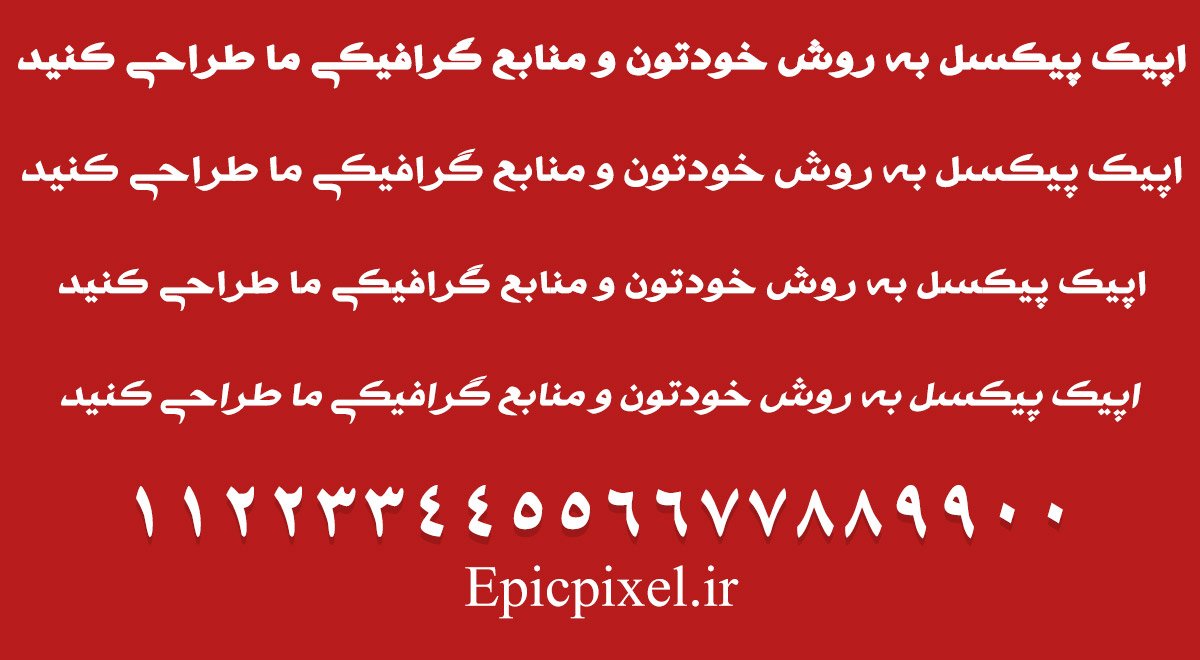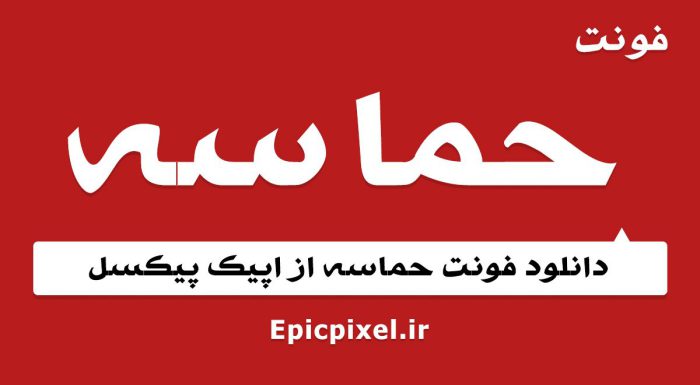
فونت حماسه فارسی
فونت حماسه، با الهام از فونت محبوب تهران و با تغییراتی ظریف و افزودن عناصر گرافیکی انقلابی، ظاهری قدرتمند و منحصربه فرد به نوشته های شما می بخشد. این فونت، با وجود شباهت هایی به فونت تهران، هویتی مستقل دارد و برای طراحی هایی که نیازمند جلوه ای خاص و متمایز هستند، گزینه ای ایده آل به شمار می رود.
یکی از ویژگی های برجسته فونت حماسه، خوانایی بالای آن در اندازه های مختلف است. چه در عناوین بزرگ و چه در متن های طولانی، حروف این فونت به راحتی قابل تشخیص هستند و تجربه خواندن را بهبود می بخشند. این ویژگی، فونت حماسه را برای استفاده در طراحی های چاپی و دیجیتال، از جمله پوسترها، بنرها، وب سایت ها و اپلیکیشن ها، مناسب می سازد.
فونت حماسه، با وجود ظاهر قدرتمندش، در برخی موارد ممکن است برای متن های بسیار طولانی و با اندازه کوچک، کمی سنگین به نظر برسد. با این حال، این ویژگی در اکثر کاربردها، به خصوص در عناوین و متن های کوتاه، نه تنها نقطه ضعف نیست، بلکه به جذابیت و تأثیرگذاری بیشتر طرح کمک می کند. اگر به دنبال فونتی هستید که هم رایگان باشد و هم به طرح هایتان روحی تازه ببخشد، فونت حماسه انتخابی عالی است. این فونت با ارائه ترکیبی از سنت و نوآوری، می تواند به نوشته های شما جان ببخشد و آن ها را از سایرین متمایز کند.